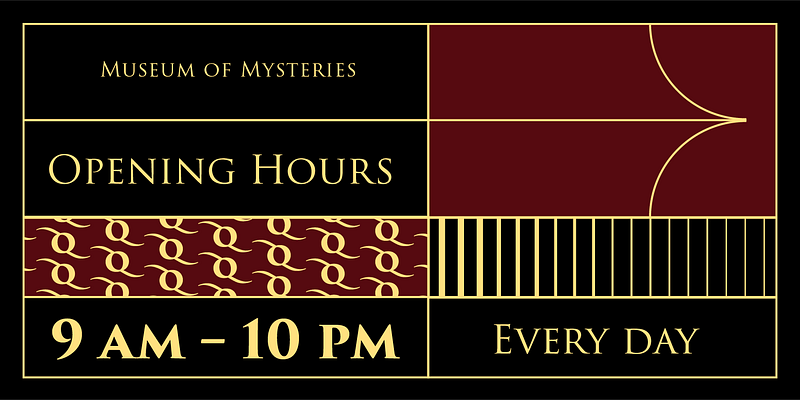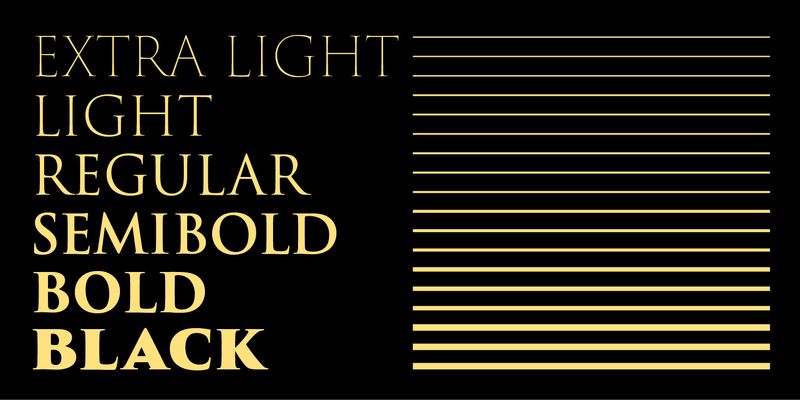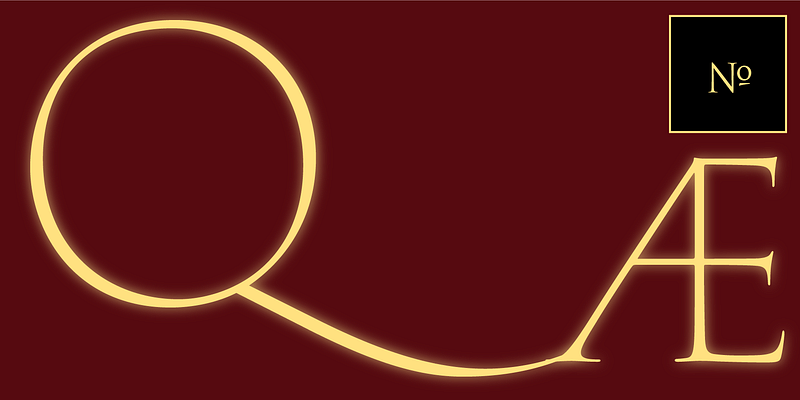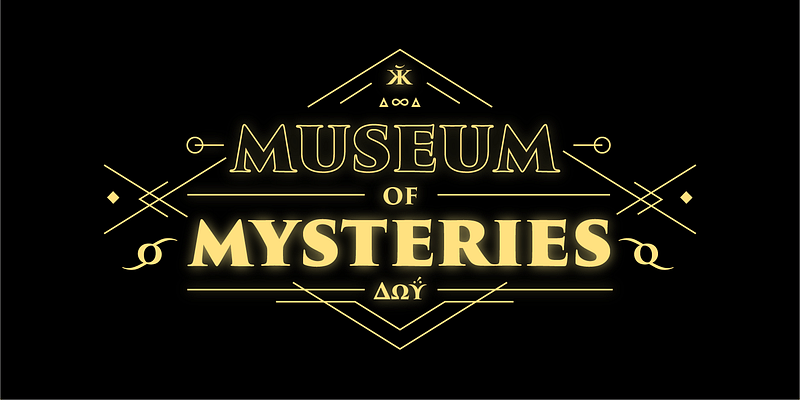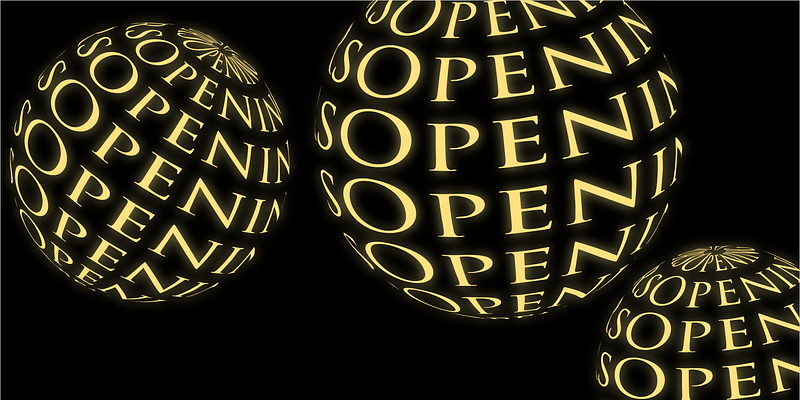
Die Inschrift auf dem Sockel der Trajanssäule in Rom ist ein Beispiel für die klassischen römischen Buchstabenformen, die ihren Höhepunkt im ersten Jahrhundert nach Christus erreichten. Es wird angenommen, dass die Buchstaben zunächst mit einem Pinsel geschrieben und dann in den Stein gemeißelt wurden. Diese Formen bildeten die Grundlage für diese Adobe Originals-Schrift, die 1989 von Carol Twombly entworfen wurde. Trajan ist eine elegante Schrift, die sich gut für die Gestaltung von Büchern, Zeitschriften, Postern und Plakaten eignet.